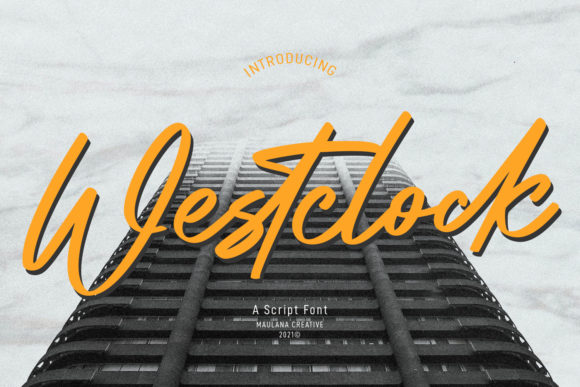
Creativefabrica Westclock Script Font 2021
[Creativefabrica] Westclock Script Font (2021)
Westclock - это шикарный, плавный шрифт, излучающий изысканность и элегантность.
Стильные чередования и лигатуры делают этот шрифт идеальным для любого проекта.